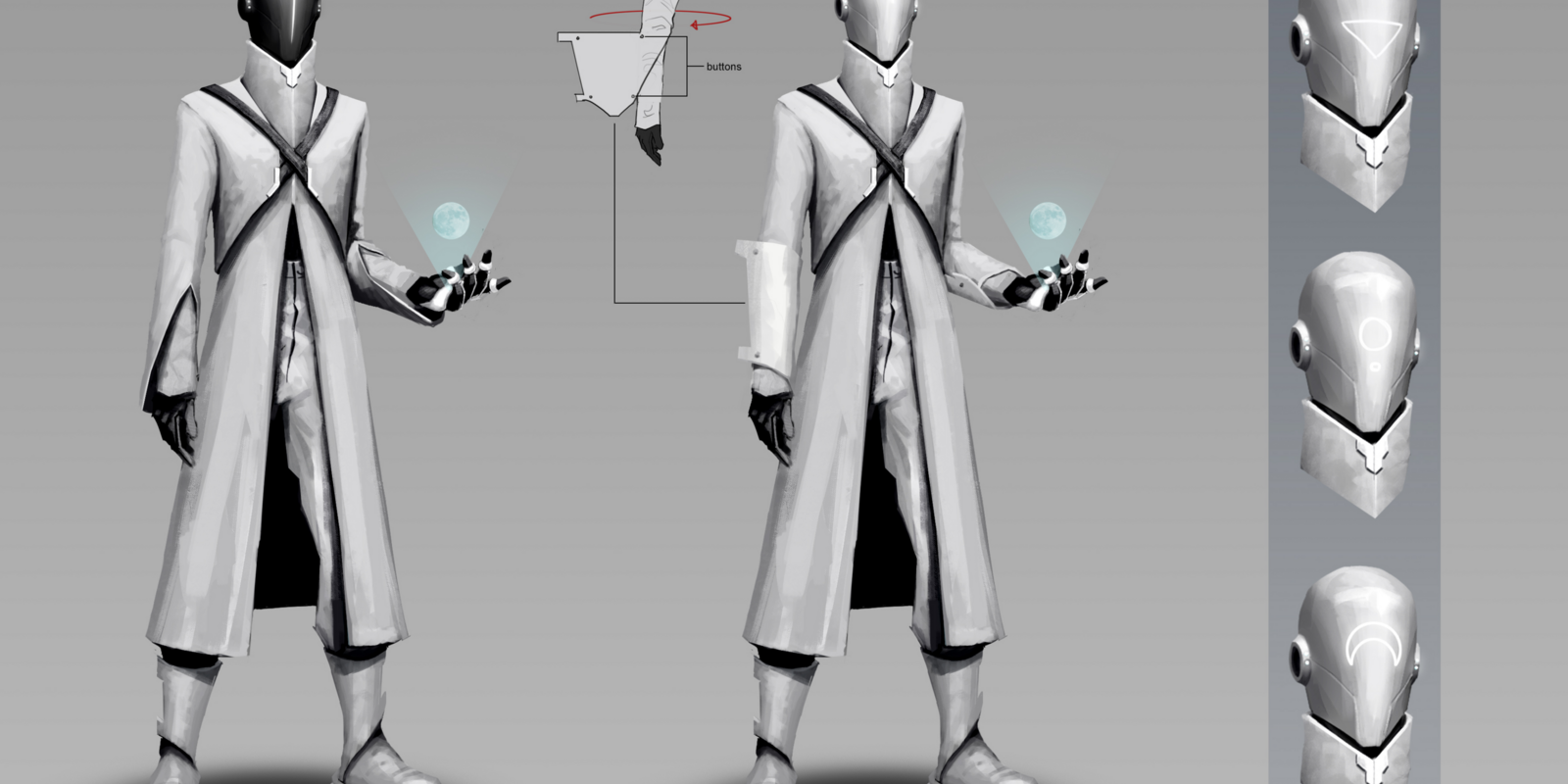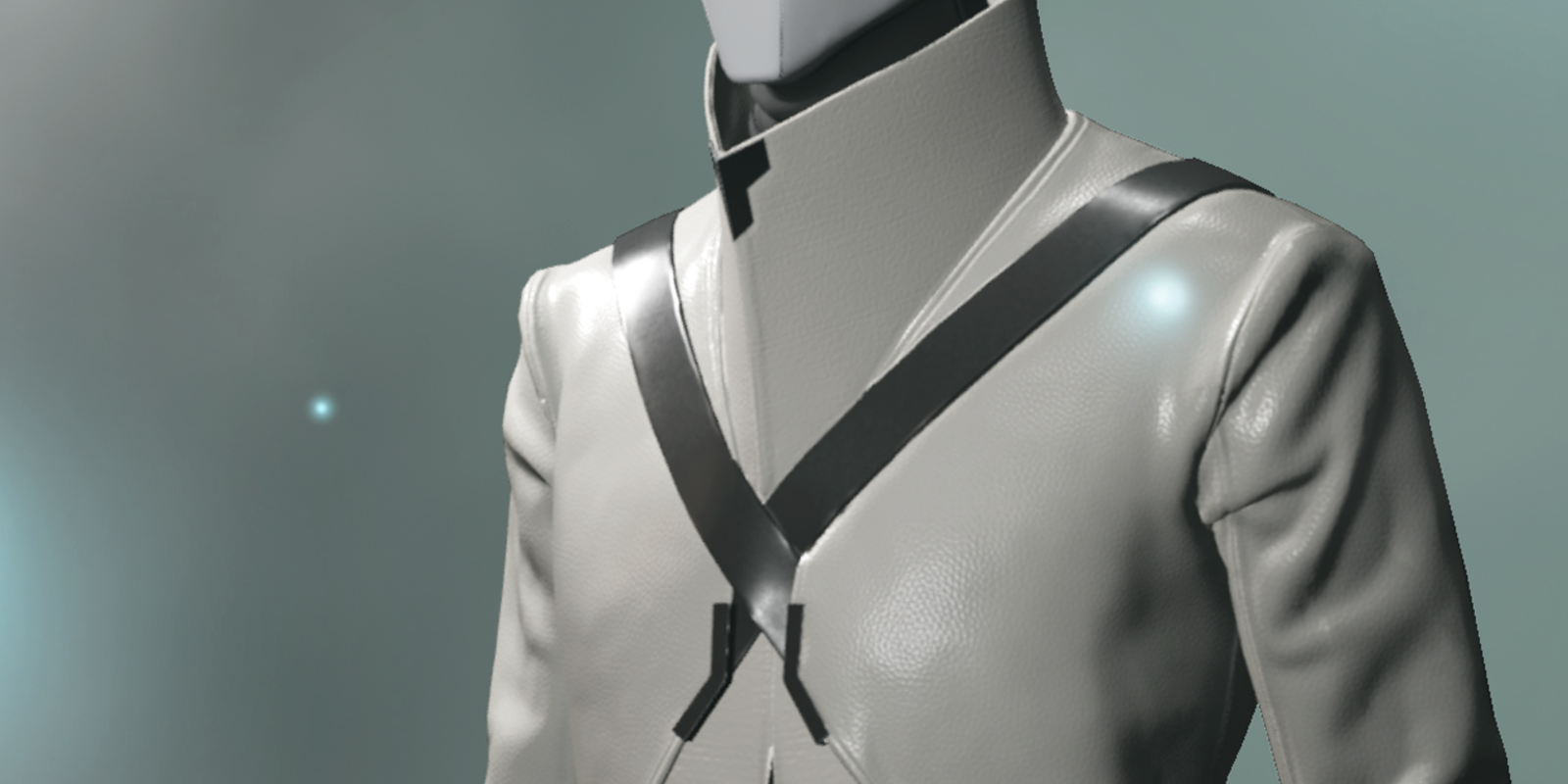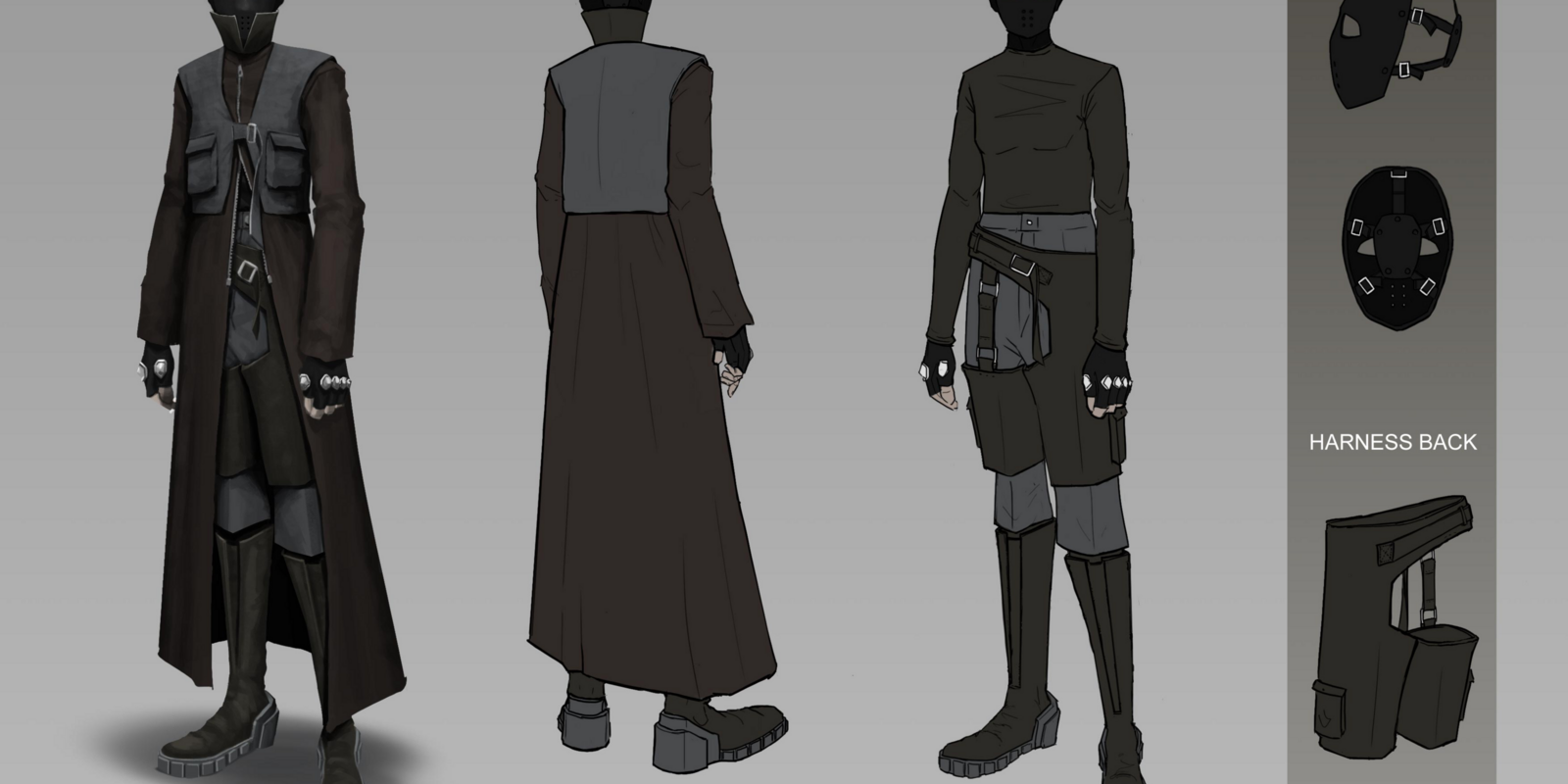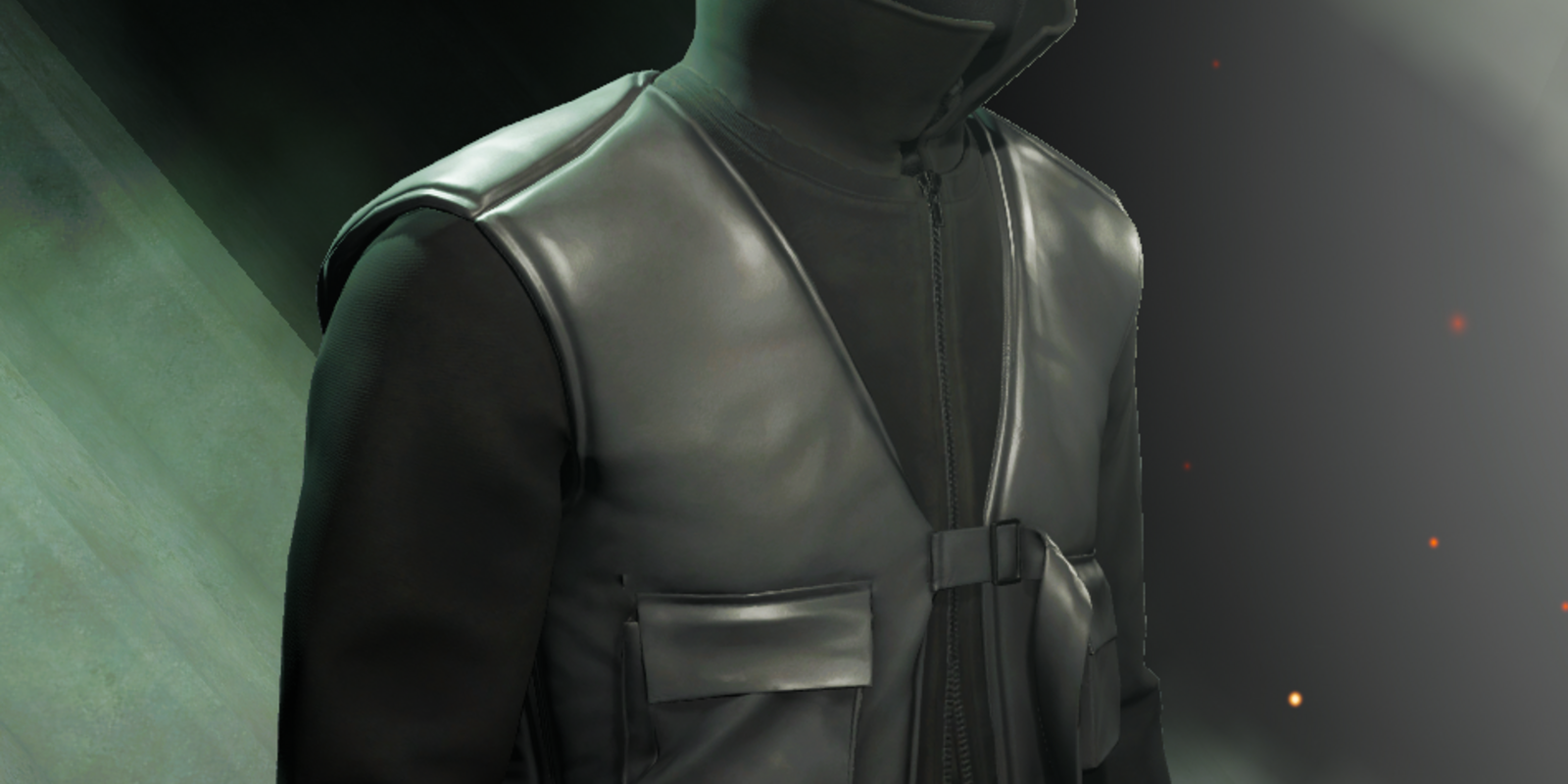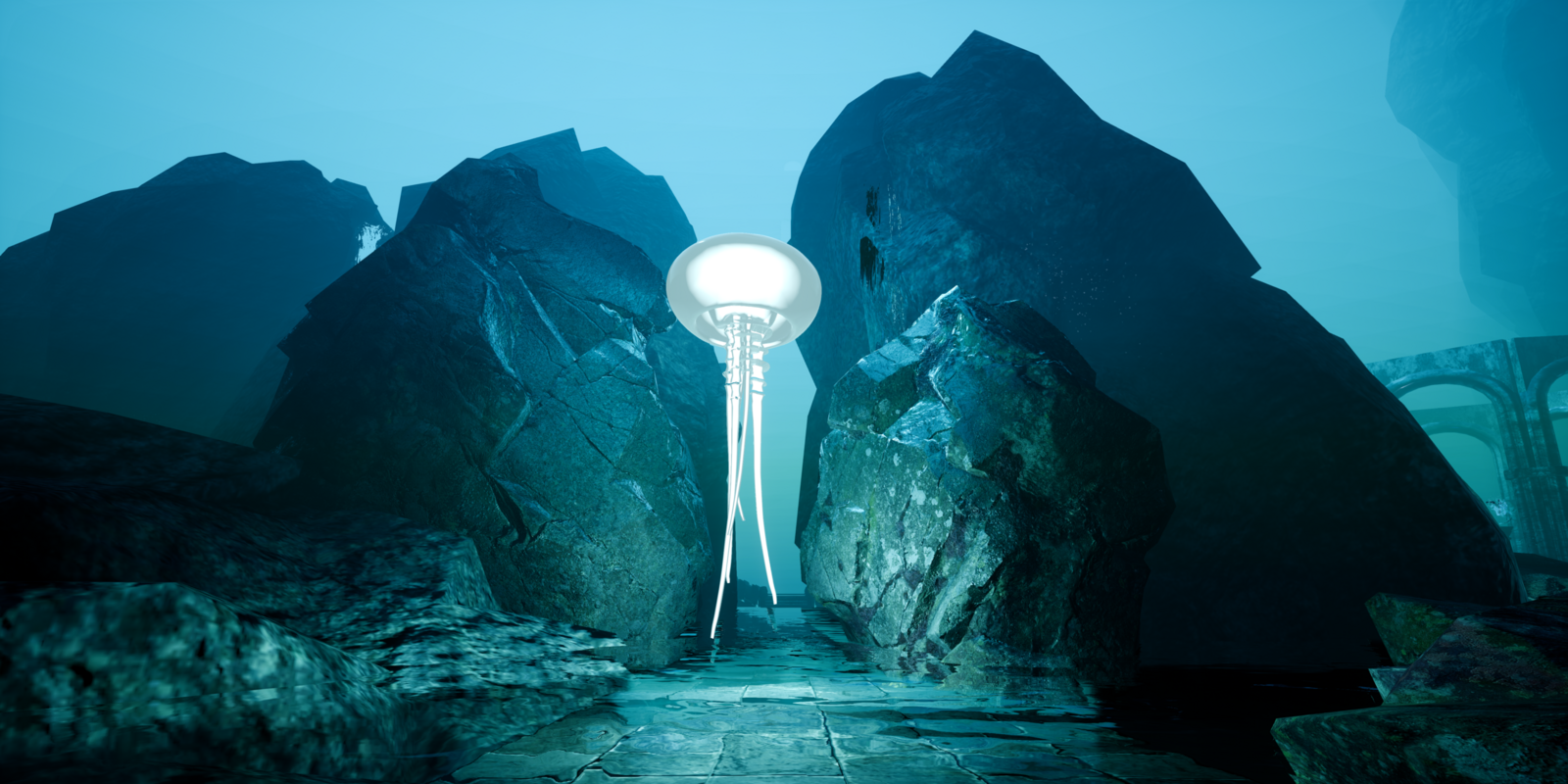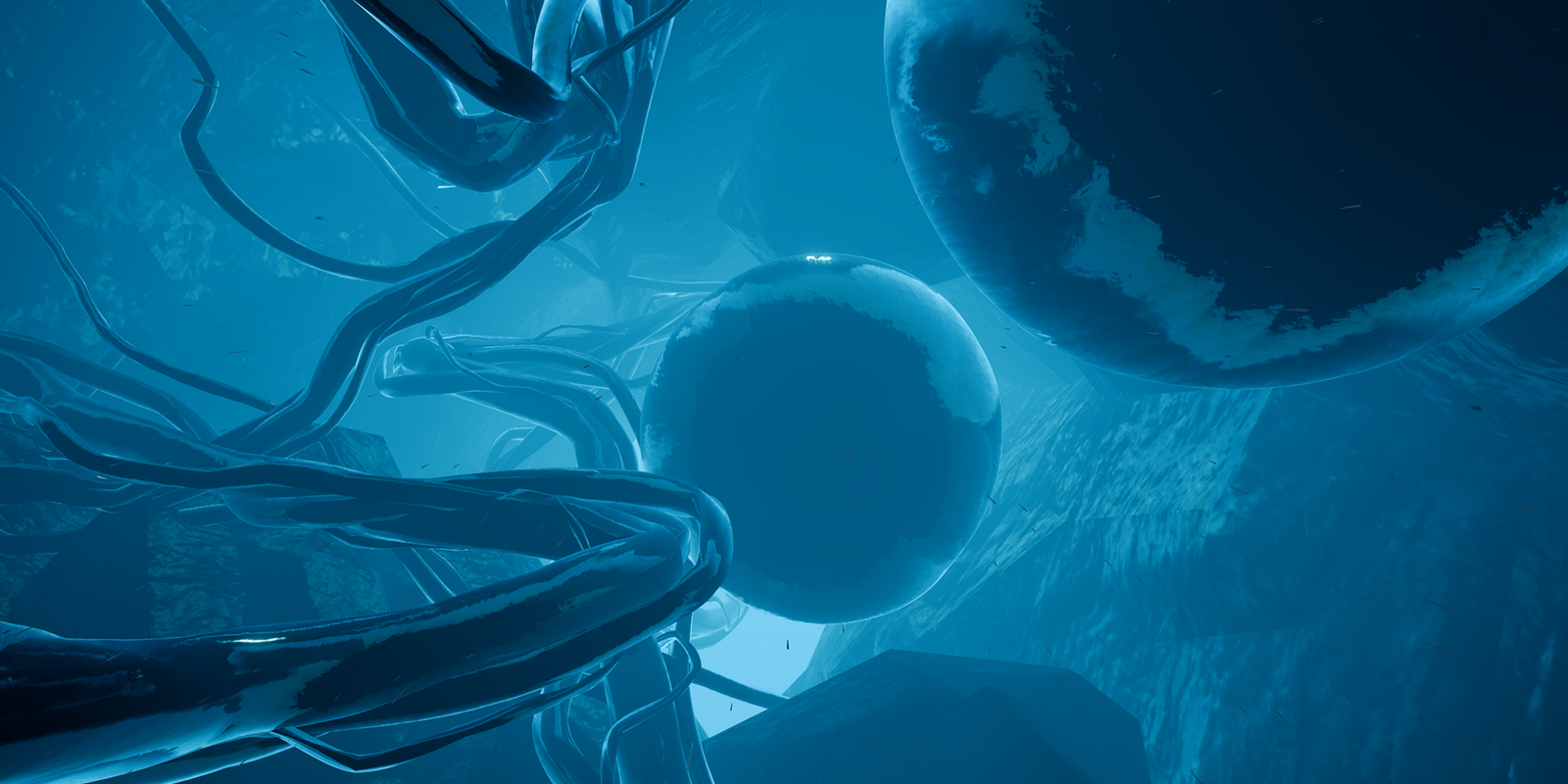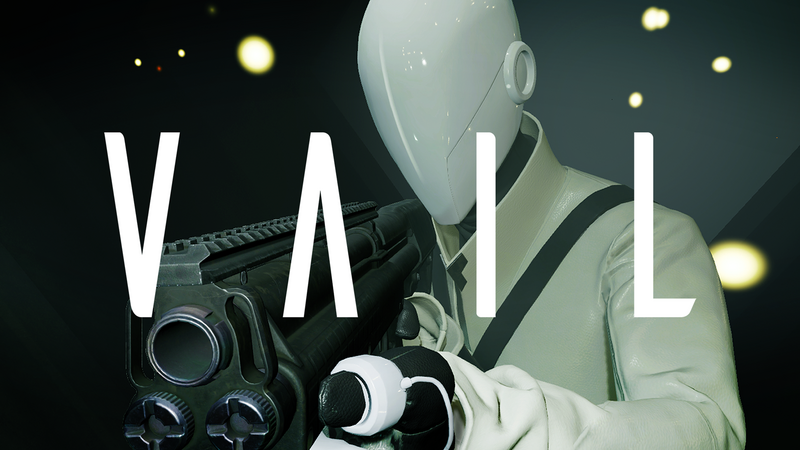
Diseñar probando: Crear conexiones profundas en mundos virtuales
En una época en la que muchos y muchas nos hemos sentido más aislados que nunca, los programas como Zoom o FaceTime, las retransmisiones en directo y los videojuegos en línea han reemplazado la socialización en persona. El uso de la realidad virtual también se ha incrementado notablemente; para muchas personas, jugar una partida virtual con otros jugadores proporciona una capa añadida de interactividad (tacto fantasma) que no puede alcanzarse por otros medios.
Llevamos tiempo estudiando el ámbito de la realidad virtual, prestando especial atención a cómo se utiliza la tipografía en los entornos virtuales.
«Nos encontramos en un momento apasionante para trabajar en este campo. Hay mucho margen para la innovación y para dar un giro a la forma de vivirlo todo, desde la música, los videojuegos y el entretenimiento hasta las experiencias sociales», afirma Elizabeth Ann Clark, directora creativa de AEXLAB, empresa desarrolladora de videojuegos en realidad virtual.
Clark supervisa la estética visual de AEXLAB y su videojuego estrella de realidad virtual, VAIL. Para ello, dirige a un equipo de especialistas en diseño visual y artistas generales, conceptuales, técnicos, de personajes y de entornos. AEXLAB también ha desarrollado experiencias de realidad virtual con anterioridad para clientes como Red Bull, el American Institute of Architects o Epic Games.
Estamos en un momento apasionante para trabajar en este campo. Hay mucho margen para la innovación y para dar un giro a la forma de vivirlo todo, desde la música, los videojuegos y el entretenimiento hasta las experiencias sociales. ”
Elizabeth Ann Clark.
En 2015, Clark empezó en el mundo del diseño de la realidad virtual, casi sin pretenderlo. Habiéndose formado como cineasta, trabajaba en el proyecto de un videojuego llamado Water Planet para un álbum que había producido, cuando alguien le sugirió transformarlo en realidad virtual. Lo que comenzó como un proyecto musical evolucionó hasta convertirse en un proyecto cinematográfico y, en última instancia, en uno de realidad virtual, para acabar aterrizando en el Institute of Contemporary Art de Miami.
Por aquel entonces, los diseñadores y diseñadoras de realidad virtual en ciernes no tenían muchos recursos, por lo que Clark y su socio y director tecnológico de AEXLAB, Albert Ovadia, recurrieron al programa Unreal Dev Grants, una comunidad de realidad virtual pequeña, pero en expansión, y dedicaron horas y horas a realizar pruebas.
«Puedes tratar de tomar decisiones de diseño similares a las que tomarías en otros medios», explica Clark, «pero no siempre se aplican los mismos principios, por lo que ha sido interesante descubrir cómo presentar la información en los mundos virtuales». En comparación con los ámbitos en 2D, cuando se diseña en el contexto de la realidad virtual, hay muchos más aspectos que abarcar, ya que los jugadores y jugadoras tienen una vista de 360 grados y pueden explorar cada centímetro del entorno con gran detalle. La otra pieza importante que hay que tener en cuenta a la hora de diseñar un videojuego de realidad virtual es la interfaz.
“ Puedes tratar de tomar decisiones de diseño similares a las que tomarías en otros medios, pero no siempre se aplican los mismos principios, por lo que ha sido interesante descubrir cómo presentar la información en los mundos virtuales. ”
Elizabeth Ann Clark.
En lo que respecta al texto presente en los mundos de realidad virtual, Clark señala que hay que tener en cuenta multitud de detalles para que no haya problemas. En AEXLAB se esfuerzan continuamente para que el texto de los menús y los minimapas de la experiencia de VAIL se lea cómodamente y se pueda personalizar según las preferencias del jugador o la jugadora. «Tienes que experimentar la realidad virtual con elementos que te resulten cómodos», apunta Clark, y afirma lo siguiente: «El tamaño o la calidad de la fuente pueden tener un efecto muy importante en la experiencia. Además, si no se hace correctamente, el movimiento puede provocar mareos, así que es un aspecto fundamental. Todavía no se ha documentado el mejor caso de uso; se está estudiando. Hay una gran cantidad de información gratuita disponible, pero creo que queda mucho margen de mejora en el diseño. En el próximo par de años veremos cómo evoluciona».
Su equipo prestó mucha atención a la selección del tipo de letra para VAIL. Albert Ovadia, director tecnológico de AEXLAB, dio con la fuente del juego, Ailerons, que no era sino la tesis final de un estudiante brasileño de diseño gráfico. El videojuego se desarrolla en un futuro próximo, en una Tierra posapocalíptica con una colonia en órbita que promete una nueva era vital. Visualmente, el juego tiene un lenguaje de diseño minimalista, con tonos principalmente monocromáticos y toques en colores de neón, así como una temática futurista y de ciencia ficción. El tipo de letra tenía que ajustarse a esa estética y funcionar bien en la experiencia de realidad virtual, y Ailerons cumplía todas las exigencias.
«Me enamoré todavía más de Ailerons (que significa “alerón”) cuando me documenté sobre su diseñador y las decisiones en las que se basaba el diseño. Es bonito porque el alerón es la parte de la mecánica responsable de que las alas de un avión se eleven y se muevan».
El diseñador tipográfico, Adilson Gonzalez, se inspiró en los aviones de los años cuarenta, lo que queda patente en un diseño que es ligero, pero tiene un acento de ciencia ficción. Clark también es partidaria de apoyar a los jóvenes diseñadores y diseñadoras, y según explica, uno de sus recursos favoritos es la biblioteca de fuentes Typelab, que recopila fuentes diseñadas por jóvenes artistas de todo el mundo.
«Las herramientas de Unreal Engine me han dado la posibilidad de crear mi propio universo. Es un momento increíble para iniciarse en esto».